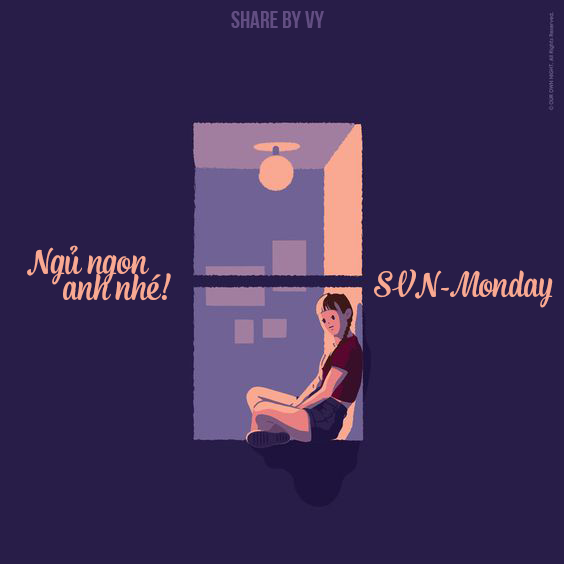
[Font] SVN Monday
Chào các bạn gần xa, lại là mình đây. Mình share font nữa này =)))) Font này khá đơn giản, nét cũng mềm khá đáng yêu. Tiện thể cho mình pr là Makani's House đang tuyển mem, CTV đó các bạn, các nhân tài hãy đ.ổ xô về nhà mình nào =))))) Vào nhà đi, font đẹp là mình share cho liền =))) (Các bạn có thể ghé qua đây _Makani nha).